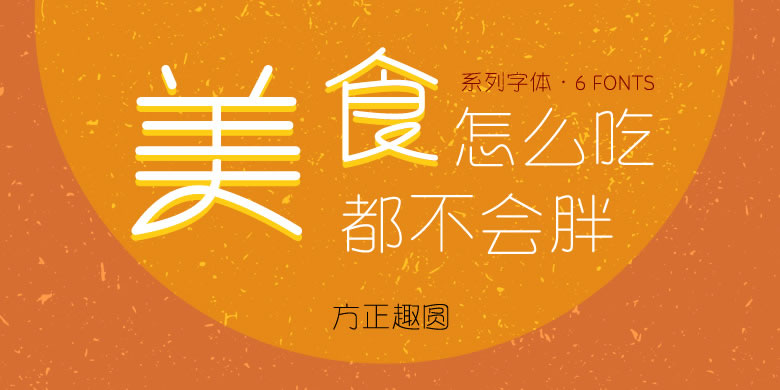
Font name:方正趣圆系列共6款
品牌: 方正字库
设计师: 胡晓波
发行时间:2017
字体介绍:
字体采用线构成的等粗笔画,融入手写连笔的创意,将字体设计的活泼有趣又不会过于卡通,适用于女性用品行业,娱乐,教育,儿童等行业用字。
包含6个字体分别是:
方正趣圆简体 Light
方正趣圆简体 Bold
方正趣圆扁简体 Light
方正趣圆扁简体 Bold
方正趣圆长简体 Light
方正趣圆长简体 Bold